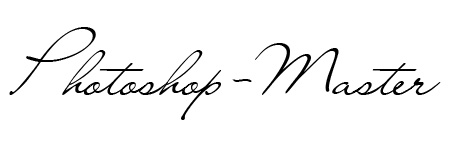
Дополнения Шрифты Татьяна Гапонова 31 марта 2009 Шрифт - Lainy Day Красивый шрифт без поддержки русского языка Скачать Шрифт - Lainy Day
красота
Почерк красивый)
суперский
очень классный шрифт!
Хороший шрифт!
Шик.